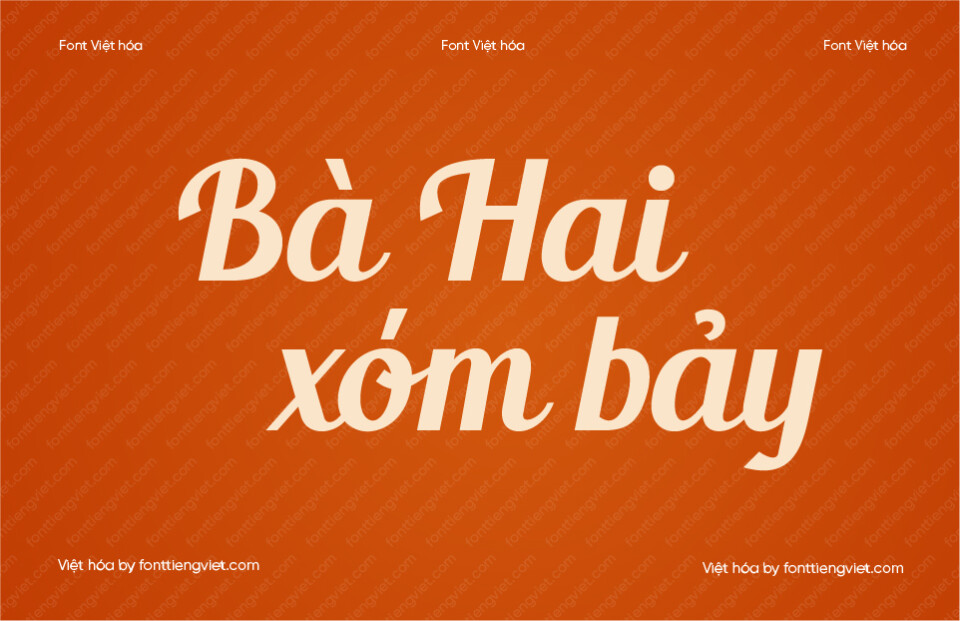
Font Việt hóa 1FTV Blenda Script
Trong thế giới đồ họa, việc tìm kiếm một bộ Font Miễn Phí có phong cách cổ điển nhưng vẫn mang hơi thở hiện đại là điều vô cùng quan trọng. Font Việt hóa 1FTV Blenda Script chính là giải pháp hoàn hảo dành cho những ai yêu thích sự mềm mại và cá tính. Đây là phiên bản được tinh chỉnh kỹ lưỡng, hỗ trợ đầy đủ bộ gõ tiếng Việt giúp các bạn học sinh và nhà thiết kế dễ dàng sáng tạo mà không lo lỗi font.
Đặc điểm nổi bật của Font Việt hóa 1FTV Blenda Script
Cảm hứng thiết kế từ Lobster
Được truyền cảm hứng từ bộ font huyền thoại Lobster, Font Việt hóa 1FTV Blenda Script sở hữu những đường nét uốn lượn tinh tế nhưng có phần mạnh mẽ và dứt khoát hơn. Kiểu chữ dạng script này tạo ra cảm giác hoài cổ của những thập niên trước, rất phù hợp cho các bài thuyết trình học tập hoặc làm thiệp mời. 1FTV Blenda Script mang lại sự chuyên nghiệp trong từng nét chữ, giúp nội dung của bạn trở nên nổi bật và thu hút thị giác ngay từ cái nhìn đầu tiên.
Ứng dụng đa dạng trong thực tế
Với bộ Font Việt hóa 1FTV Blenda Script, bạn có thể ứng dụng vào rất nhiều mục đích khác nhau. Từ việc thiết kế logo, làm bìa sách cho đến trang trí các dự án trường học, font chữ này luôn giữ được độ sắc nét và tính thẩm mỹ cao. Nhờ bản Việt hóa chuẩn, người dùng có thể gõ các dấu thanh tiếng Việt một cách mượt mà, đảm bảo tính nhất quán cho toàn bộ văn bản thiết kế.